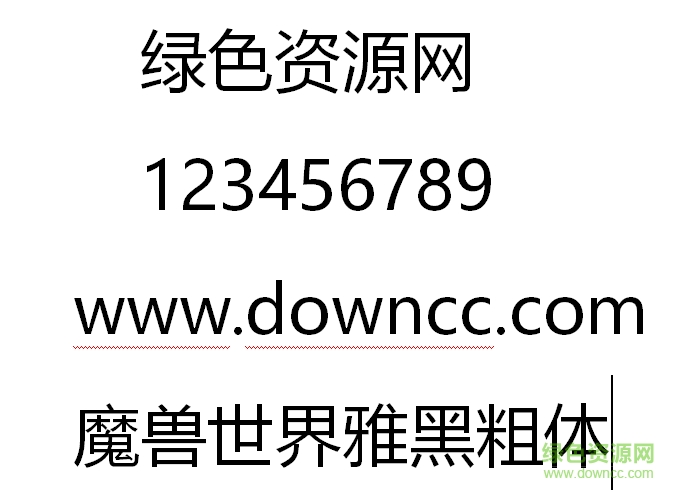
魔兽世界雅黑粗体是一款由微软公司设计的中文字体,这款字体十分美观,常用于游戏设计,许多魔兽世界游戏玩家都非常喜欢这款字体,有需要的用户赶快来本站免费下载使用吧!
微软雅黑是windows系统的默认字体,开始只有微软雅黑Regular、微软雅黑blod、微软雅黑Light 几种字重,后来微软在Windows 10 RS4下重新设计了微软雅黑,并增加了微软雅黑SemiLight、SemiBold和Heavy字重。微软雅黑新字体看起来既像苹方,又像思源黑体,还像冬青黑体。即使没开Cleartype,也能得到(几乎)完美的效果。